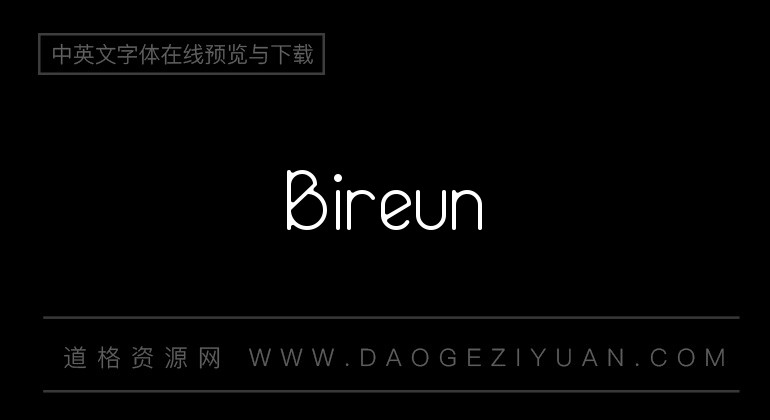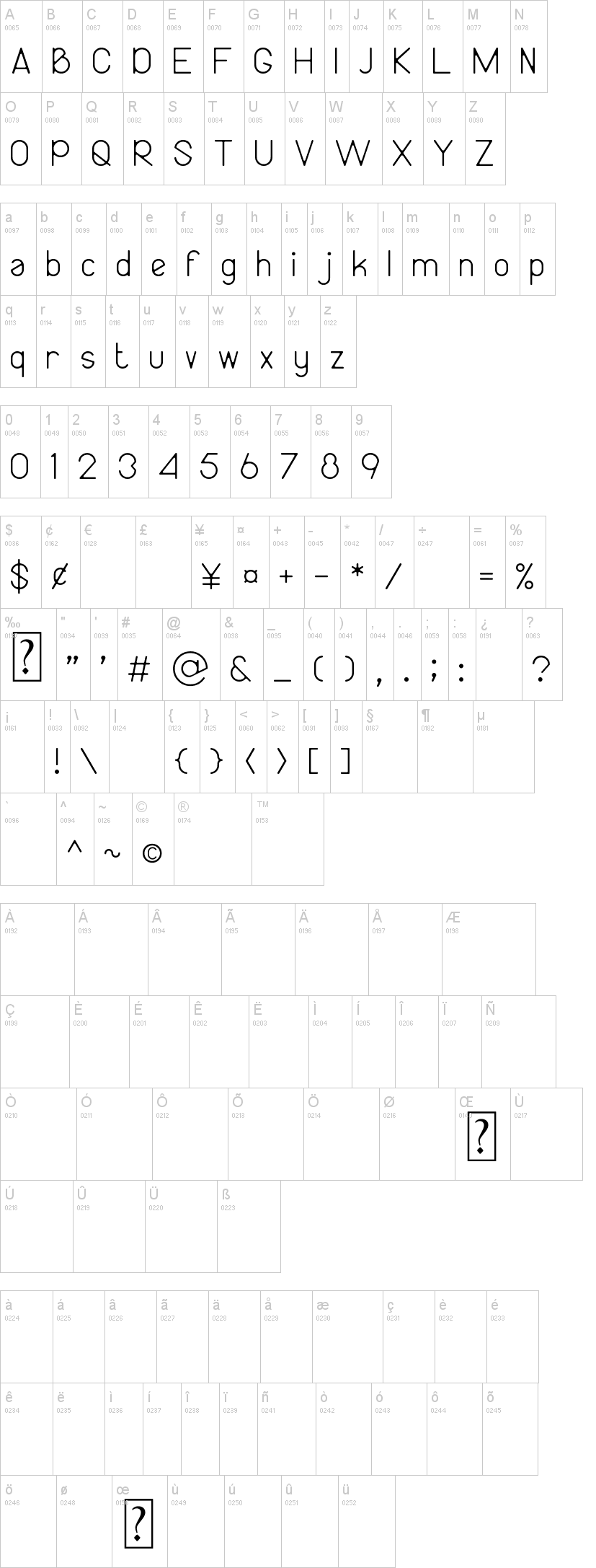
Bireun 是一款简洁、清新的字体,由荷兰设计师Jeroen van Eerden设计。它的外观柔和而精致,适合用于报纸、杂志、海报、广告等印刷品的设计。它具有独特的英文字母和数字,以及其他几何图形,可以为您的设计提供更多的选择。此外,它还提供多种字体大小,可以满足您的个性化需求。内容介绍
Bireun是一款非常不错的手写艺术字体,具有很好的视觉感,适合于文化类的宣传设计、商业类品牌的广告和产品包装设计以及个性化文字排版等较多场景。